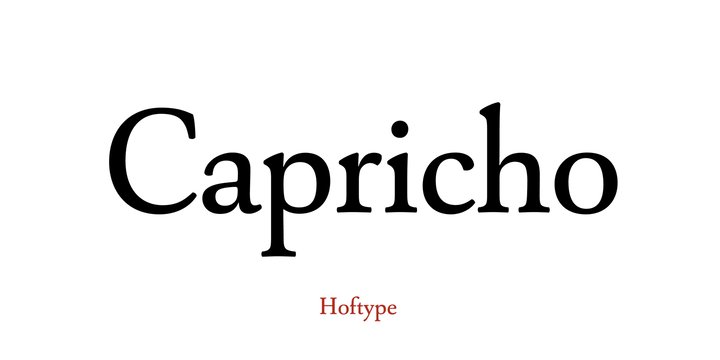
Myfonts Capricho Font
[Myfonts] Capricho Font
Capricho - это теплый, уютный и приятно читаемый шрифт.
Он объединяет в себе достоинства переходного шрифта 17-го века с его собственным отличительным и индивидуальным вкусом.
Его крупные нисходящие и восходящие элементы придают ему выразительный вид.
Дополняющий его курсив с плавно перетекающим дуктусом является контрастным контрапунктом.